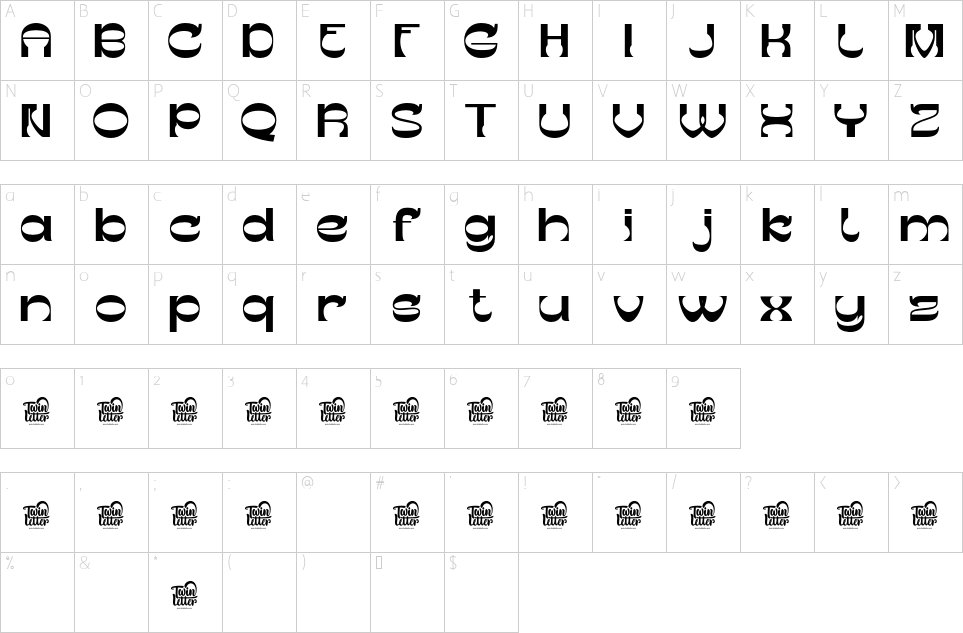
A fonte Gesego é uma escolha elegante e moderna para designers e amantes da gráfica. Desenhada por um talentoso designer não identificado, ela oferece um equilíbrio perfeito entre ser minimalista e sofisticada. Seu design foi cuidadosamente construído para garantir uma legibilidade perfeita em diferentes tamanhos de texto. Com seu design limpo e moderno, Gesego é uma ótima opção para qualquer projeto que exige um acabamento de alto padrão. Com 1.552 downloads até o momento, é evidente que os designers estão se beneficiando da simplicidade e da elegância desse belo design. Seja para criar uma marca forte, desenvolver um layout memorável ou simplesmente aperfeiçoar a aparição de seu projeto, a fonte Gesego é uma fonte gratuita que vale a pena experimentar.